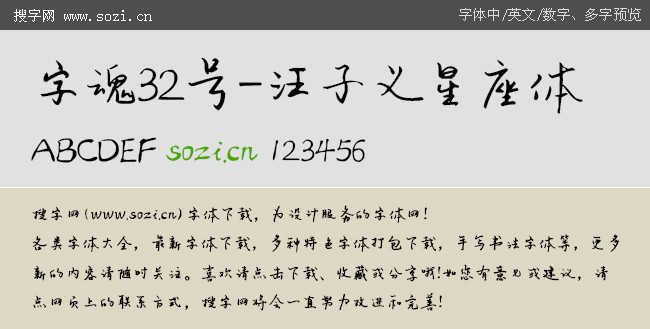
字魂32號(hào)-汪子義星座體
搜字網(wǎng)提供一款字魂32號(hào)-汪子義星座體中文字體下載,該字體是一款硬筆手寫字體,該字體包含6763個(gè)中文、字母、 符號(hào)和數(shù)字,具有復(fù)古、古典、創(chuàng)意 的風(fēng)格,可以滿足您設(shè)計(jì)上的各種需求,該字體主要用于企業(yè)店鋪、廣告、新媒體、電商雜志、圖書、H5 等場(chǎng)景。